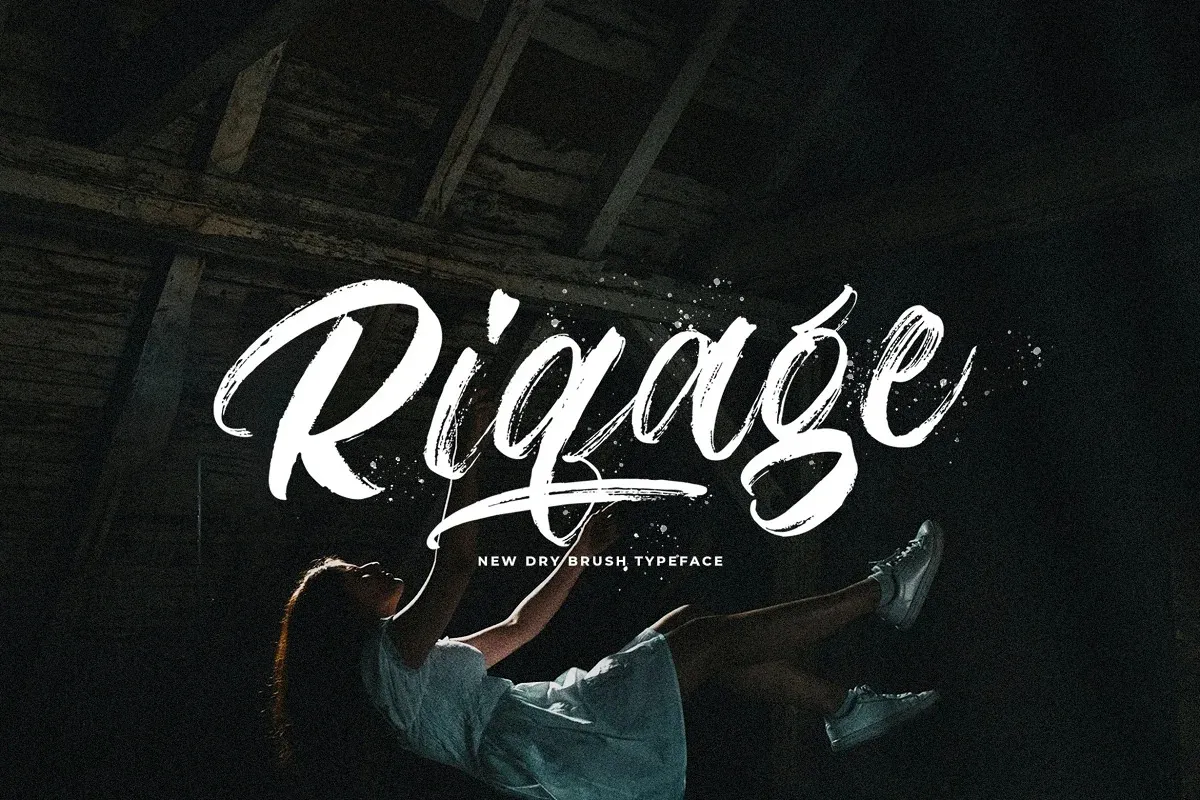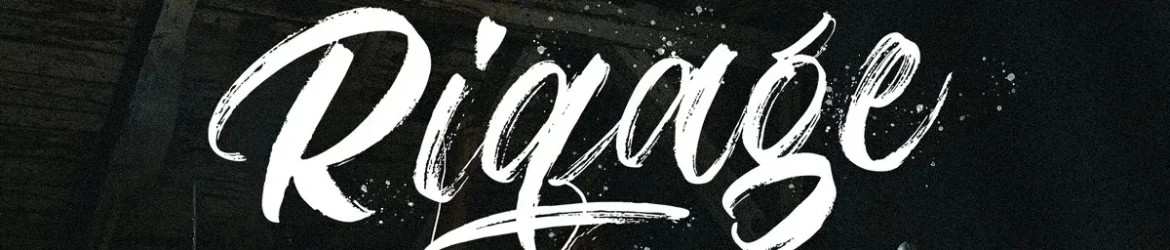
A Riqage Font é uma nova tipografia moderna criada pela StringLabs com uma linha base irregular, que oferece uma abordagem contemporânea ao design e um toque naturalmente elaborado. A fonte está projetada para uso em aplicações variadas onde requere um ar de autenticidade e sofisticação, como capas de roupas, convites, títulos de livros, cartões de papelaria, citações, marcas de marca, logotipos, camisetas, embalagens e panfletos. Com uma cobertura completa que inclui letras maiúsculas e minúsculas, além de suporte para múltiplas línguas, números, pontuação e ligaduras e swashes adicionais, a Riqage Font é um recurso versátil que pode ser usada em inúmeras situações criativas. Perfeita tanto para trabalhos digitais quanto para impressão, ela se destaca como uma opção única para quem busca estilo natural na tipografia.